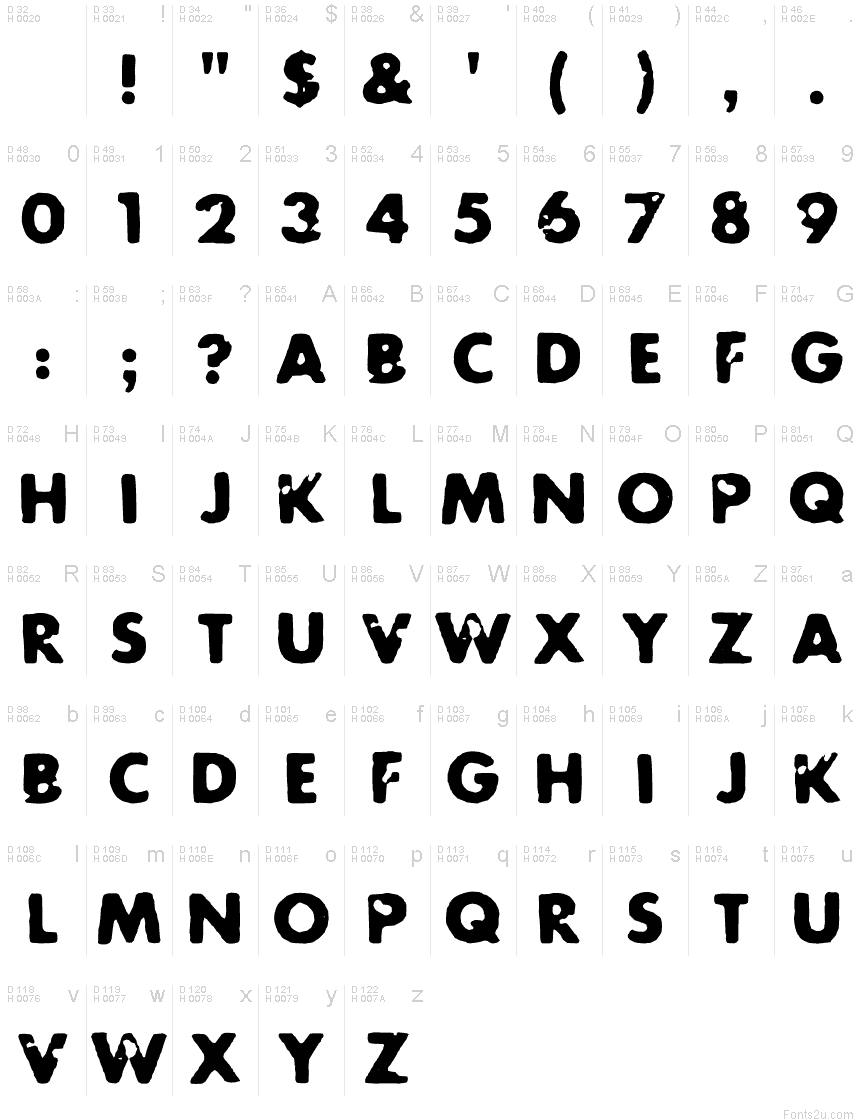
Future Rot od Footnote Fonts to darmowy, erozyjny krój display. Grube, nasycone tuszem pociągnięcia wyglądają, jakby zostały odbite i przeciągnięte po surowym betonie, pozostawiając miękkie, stopione krawędzie i ślady niszczenia w każdej literze. Efekt jest surowy i ręcznie wykonany – jak znak ostrzegawczy odnaleziony w zrujnowanej bazie science‑fiction lub plakat punkowego koncertu zerwany z wilgotnej ściany piwnicy.
Dzięki Future Rot Twoje nagłówki natychmiast zyskują surową, post‑apokaliptyczną energię, której trudno podrobić. Ten darmowy font świetnie sprawdzi się na plakatach horrorów, okładkach albumów punkowych lub metalowych, w zinach, brandingu marek skate czy streetwear, grafikach do escape roomów oraz tytułach dystopijnych gier. Użyj go w dużym formacie, aby wydobyć teksturę, i zestaw z prostym, geometrycznym krojem bezszeryfowym w tekście głównym, by pozwolić jego brudnemu charakterowi dominować.